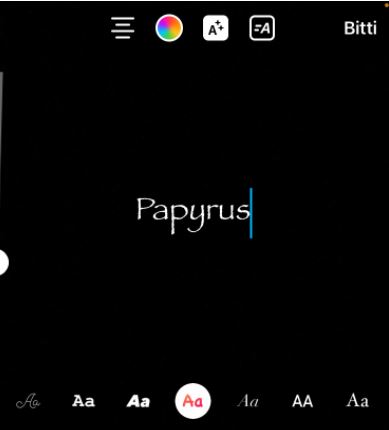
Instagram'ın gizli yazı tipi nasıl kullanılır? İşte kimsenin bilmediği Instagram'ın gizli özelliği!
Instagram'da muhtemelen çoğu kullanıcının haberi bile olmadığı bir özellik mevcut. Facebook'un satın aldığı Instagram, kullanıcılarına haber vermeden sessiz sedasız bir 'yazı tipini'...
Instagram'da muhtemelen çoğu kullanıcının haberi bile olmadığı bir özellik mevcut. Facebook'un satın aldığı Instagram, kullanıcılarına haber vermeden sessiz sedasız bir 'yazı tipini' uygulamaya ekledi.Instagram'da hikaye paylaşımı yaparken, kullanıcılar hikayesine yazı ekleme özgürlüğüne de sahip. Ancak bu yazı ekleme kısmında kullanıcılar sınırlı sayıda yazı tipleriyle yetinmek zorunda. Fakat Instagram geliştiricileri uygulamaya gizlice bir sürpriz yumurta yerleştirmiş. Bu sayede hikayelerimizde katalogda yer almayan bir yazı tipini kullanabiliyoruz.
Instagram'ın gizli fontu "Papyrus" nasıl kullanılır?
Instagram'a gizlice eklenen yazı tipi "Papyrus", 1982’de Chris Costello tarafından tasarlandı. Comic Sans ile birlikte kullanıcılarla buluşmuş olan bu yazı tipi Windows 98'lerde oldukça meşhurdu. Şimdi ise karşımıza Instagram hikayelerde çıkıyor.Papyrus fontunu şu anda sadece iOS kullanıcıları kullanabiliyor. Ancak yakın zamanda bu gizli özellik Android'e de gelecektir.
İşte gizli Papyrus yazı tipini kullanmak için yapmanız gerekenler:
1- iOS işletim sistemine sahip cihazınızdan (Android, iPad) Instagram uygulamasını açın.2- Hikayeler sekmesine girin.3- Sağ üst köşede yer alan “Aa” ikonlu metin seçeneğine tıklayın.4- Comic Sans yazı tipine gelin.5- Ekrana Papyrus yazın.Ve karşınızda yeni yazı tipi Papyrus.